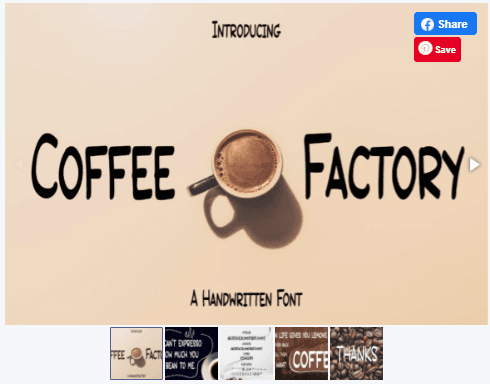
Coffee Factory Font
Coffee Factory - простой и естественный рукописный шрифт. Его можно использовать для различных дизайнов, особенно неформальных или дружеских. Добавьте его уверенно в свои проекты, и вы не разочаруетесь.